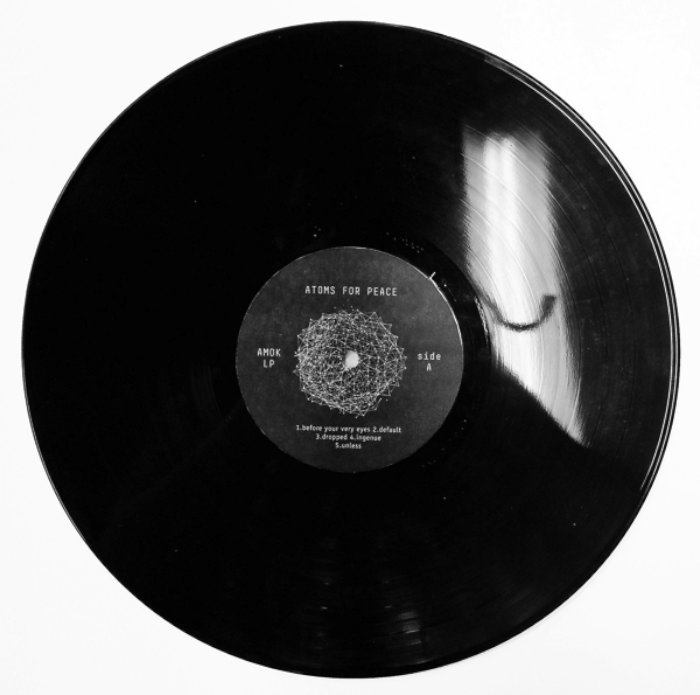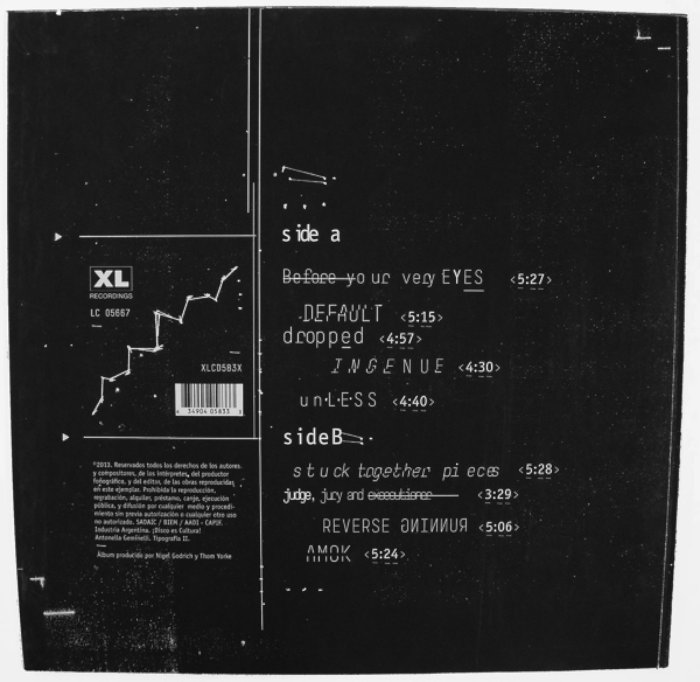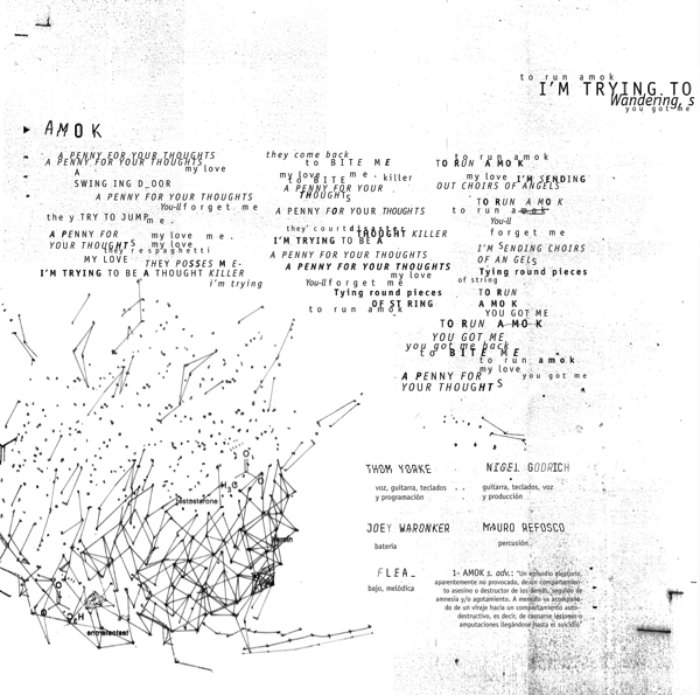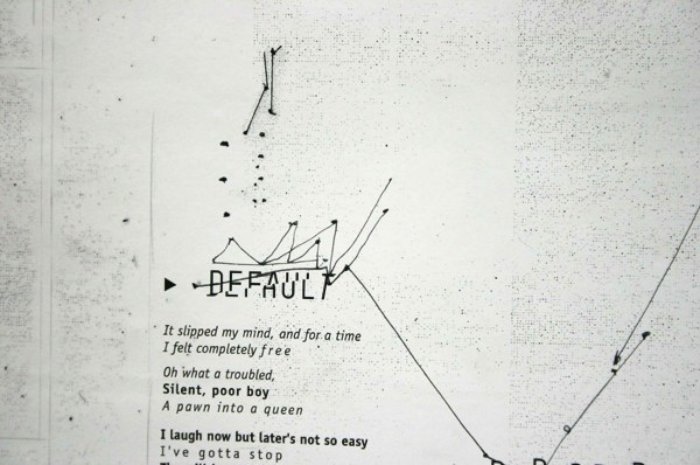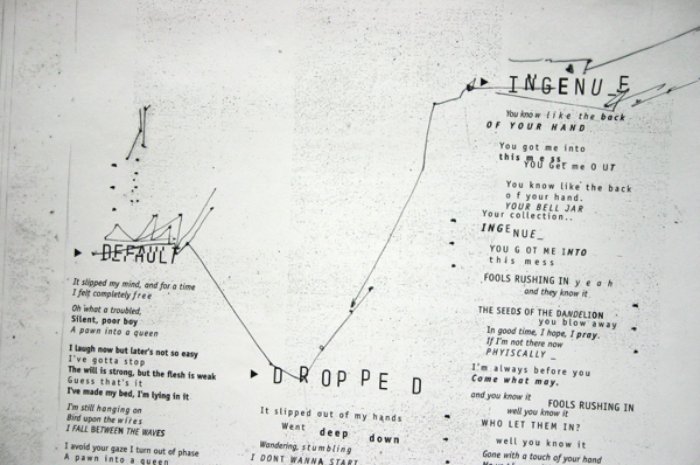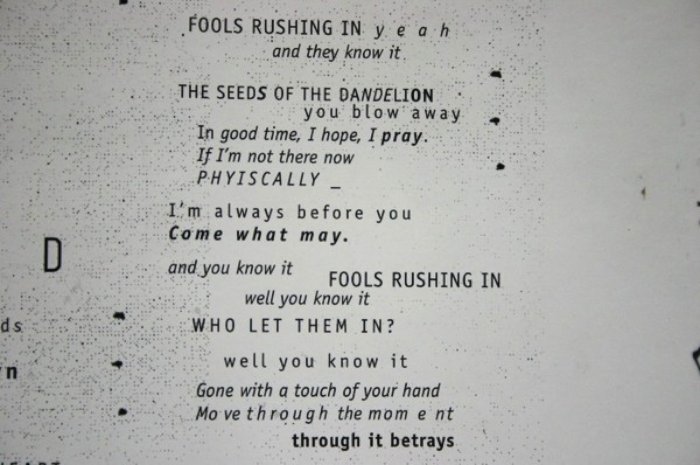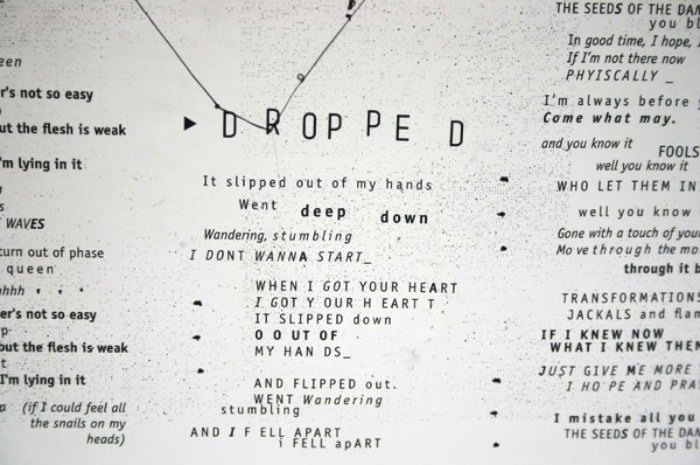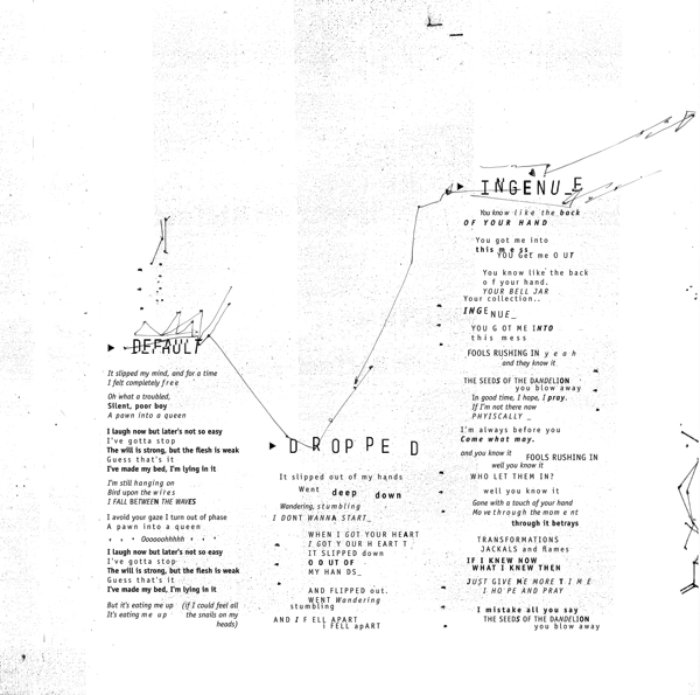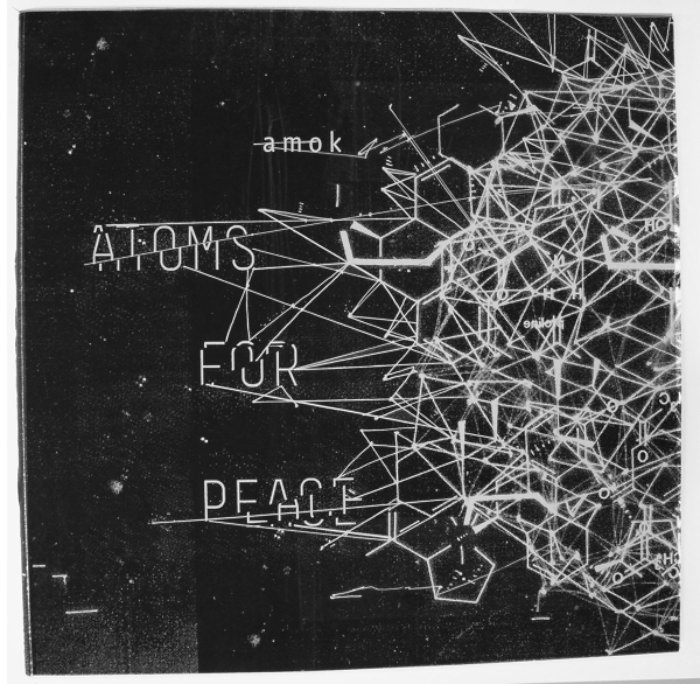
Antonella Geminelli criou o visual desse disco do Atoms for Peace na aula de tipografia da Cátedra Cosgaya em Buenos Aires, Argentina. Gostei da variação tipográfica que lembra um pouco a forma com a qual as músicas desse disco são cantadas. Gostei do visual moderno mas simples de todo o material e beleza do acabamento cru que vejo por ali.